七夕的美,像字体一样多样而迷人。每一种字体都能展现出独特的七夕情怀,仿佛是一封情书,将深情厚意写进每一个笔画。愿我们在七夕之夜,也能找到爱的归宿,共度幸福时光。让爱在不同的字体间流转,绽放出属于七夕的美丽篇章。
三极虎啸体笔画造型别出心裁,刚硬锐利,带有狂放的肌理笔触。以尖角收笔,特点突出,浑厚洒脱,磅礴之感在笔尖肆意挥洒。
Aa破阵子字体力求笔画流畅、字形饱满,用笔连续多变,风格癫狂洒脱。
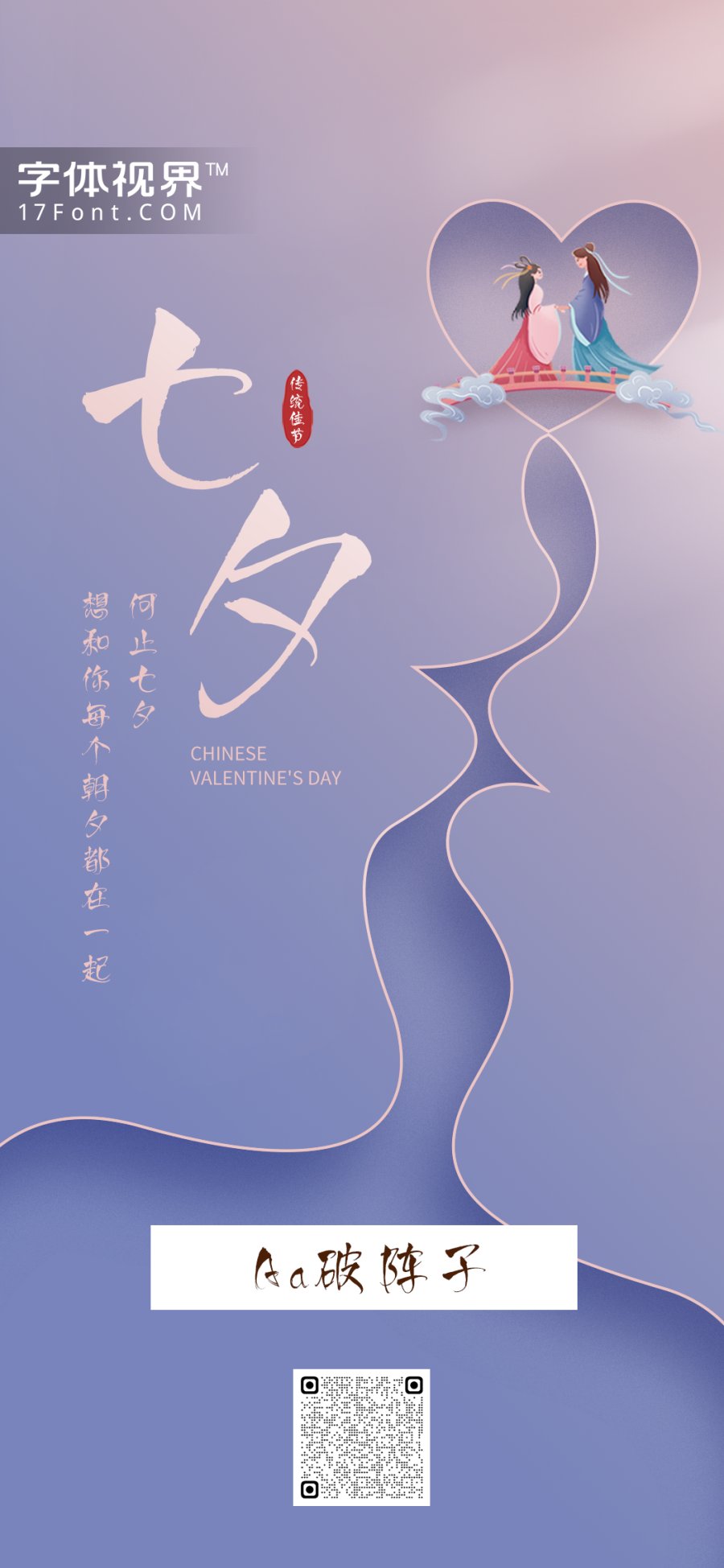
Aa闲侠少年字形端正美观,连笔自然优美,保留了连笔之间的细丝,使整个字更加灵动了。